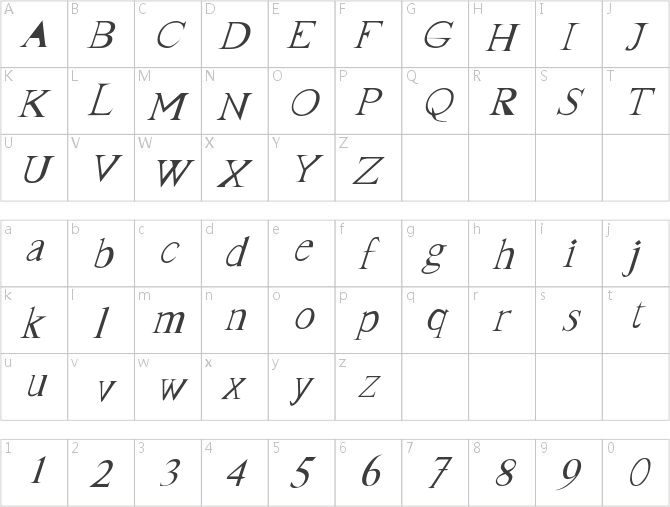
Blankboxer-Italic 詳情頁
字體名稱: Blankbo
Blankboxer-Italic
Blankboxer-Italic介紹
Blankboxer-Italic字體字庫是一款讓人賞心悅目、百看不厭的英文字體,適合各類廣告和產品包裝設計應用,字體大小0.07MB,格式為ttf字體,上傳用戶是惠祥博達,作者/版權方為未知